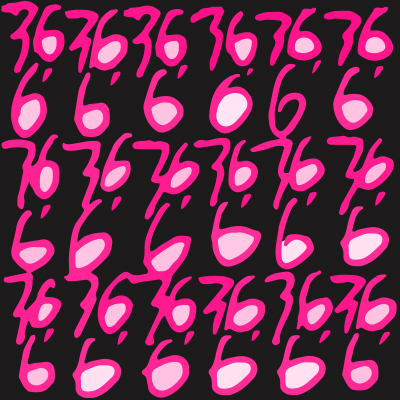
平熱36.6℃ PINK
Artist河合真里
Designer井上 智絵
Organization工房ぱれっと
36.6℃はアーティストのその日の体温を表しています。そして彼女の「今」であり、彼女自身を表します。社会が変容した今、自分をみつめなおす機会も増えたのではないでしょうか。ひたむきに、生きていこう。今日も一日、あの人も元気に過ごせますように。そんな願いも込め、デザインをしました。(井上 智絵)
コロナ禍で体温測定が日常になりました。体温記録表を埋めていくうちに、模様に見えてきました。繰り返し繰り返し書くうちにいつしか楽しくなって、両手を広げるくらいの大きな紙を埋め尽くしました。(工房ぱれっと)